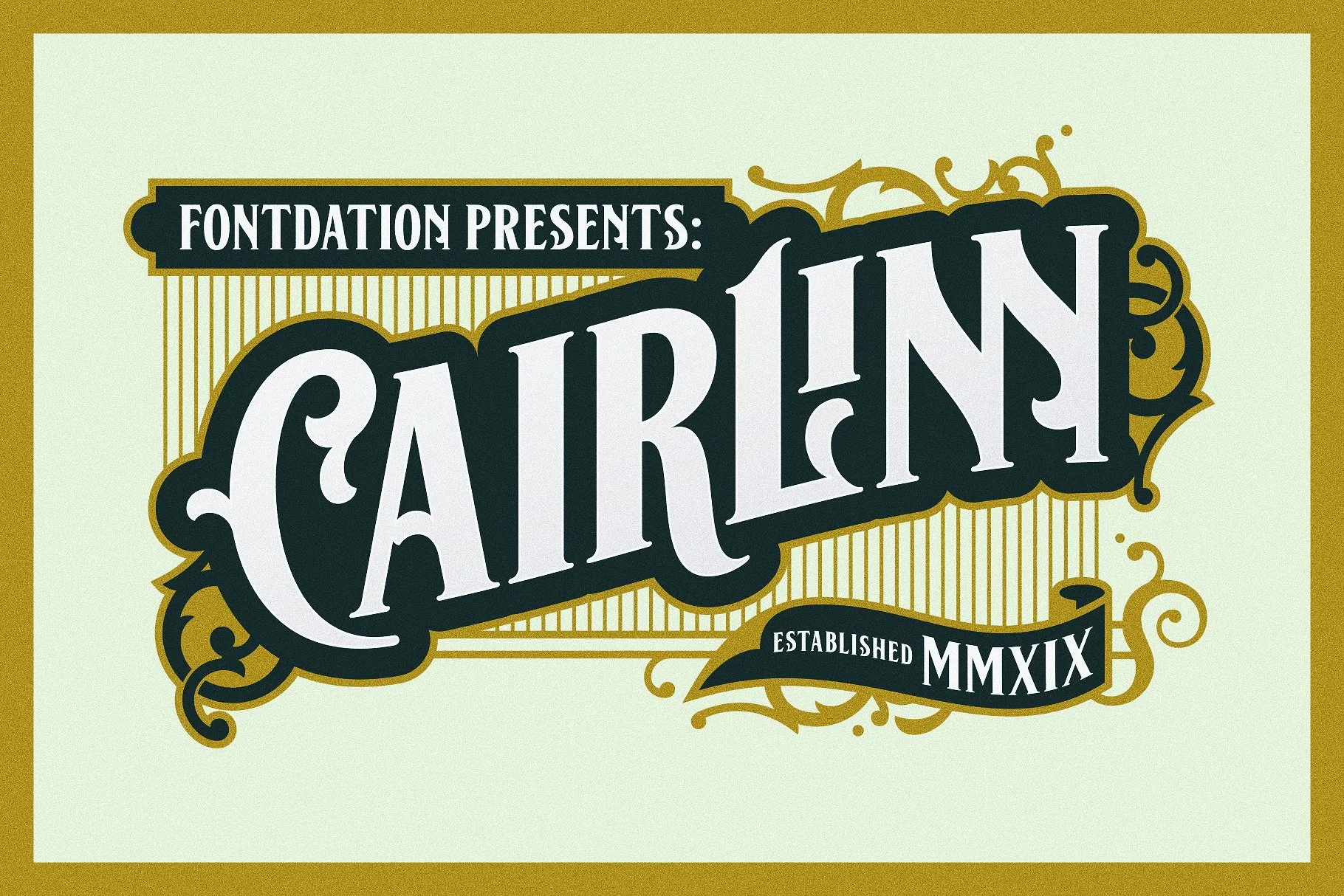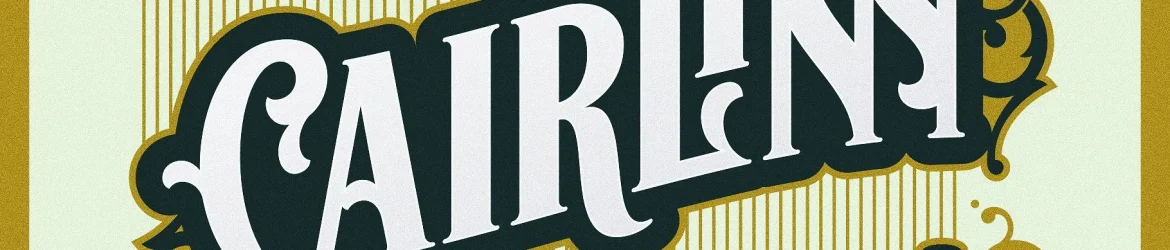
A Cairlinn Vintage Font é perfeita para quem quer dar um toque vintage aos seus projetos design. Introduzida por Twicolabs Fontdation, esta fonte original faz com que qualquer trabalho adquira um ar de autenticidade vintage. Inspirada em letras antigas usadas nos anúncios clássicos, a Cairlinn é uma serif limpada que mantém o espírito da tipografia vintage. Possui 300+ caracteres e oferece grande variação de letras através das funcionalidades OpenType. Ideal para projetos como etiquetas, design de camisetas, citações typográficas, embalagens, cartões de casamento e muitos outros que necessitam de um toque vintage. Uma fonte perfeita para aqueles que buscam algo único em seu próximo projeto de design.